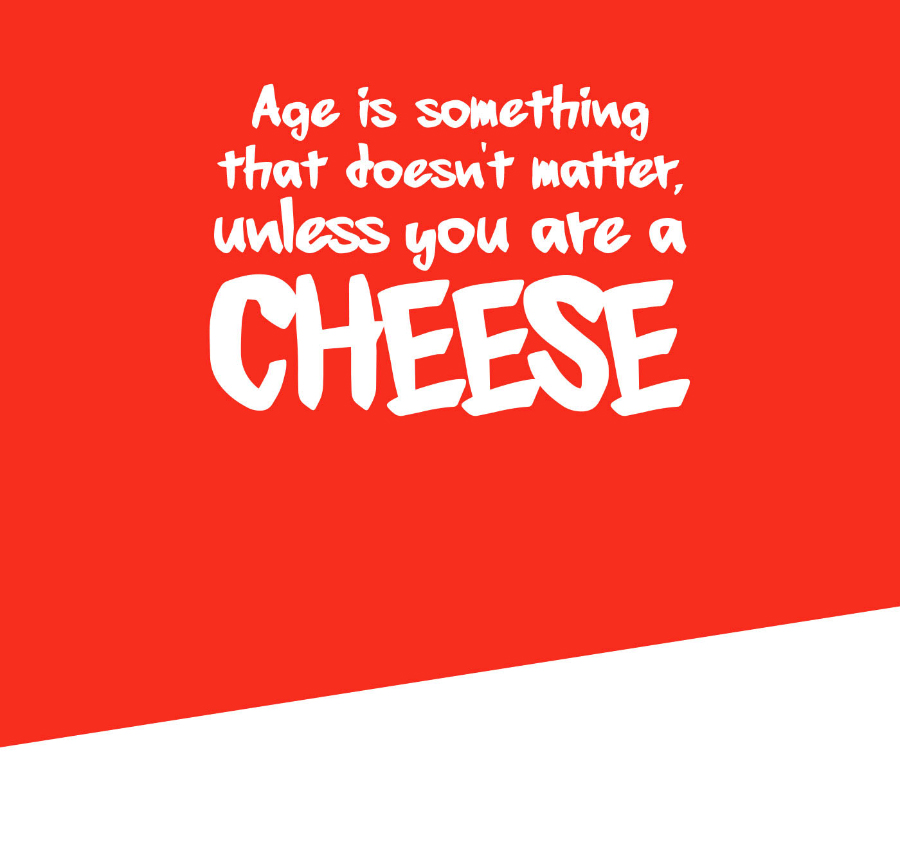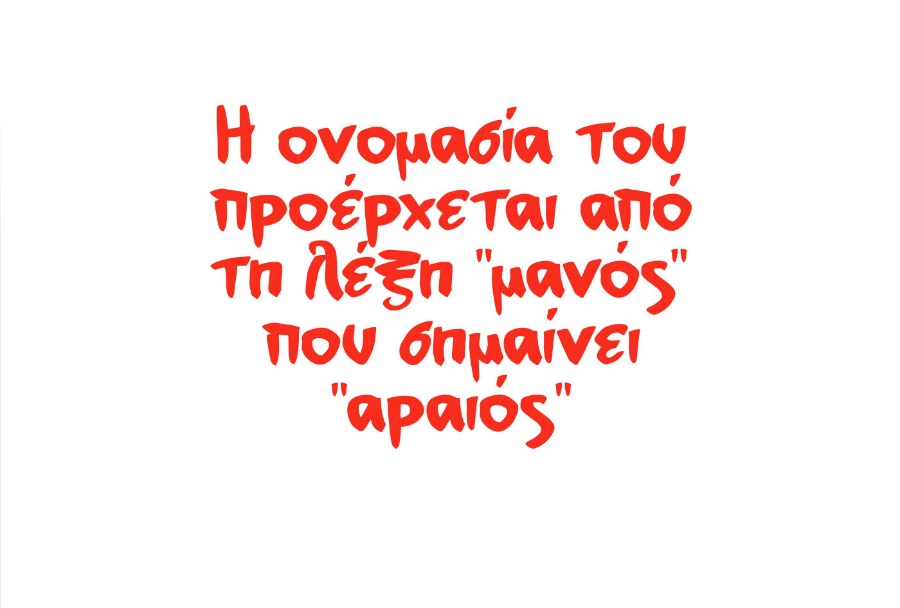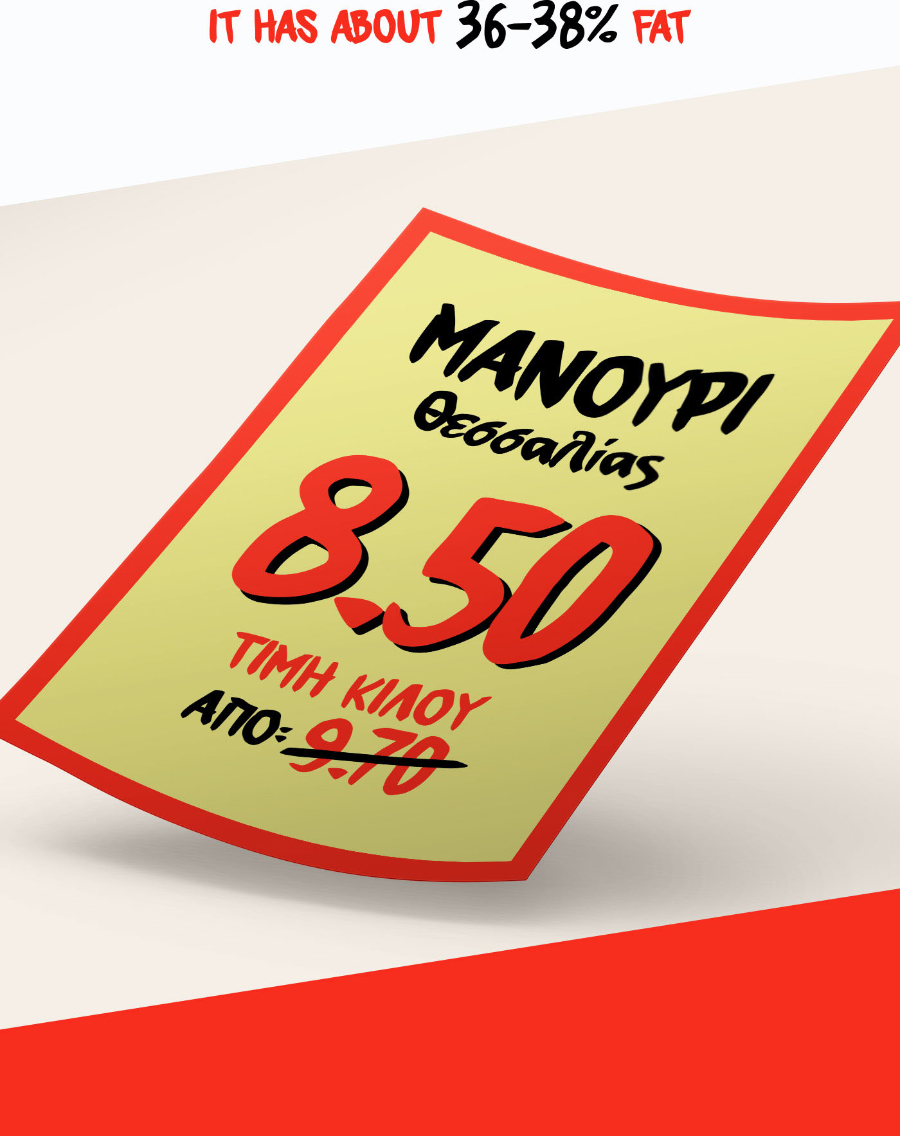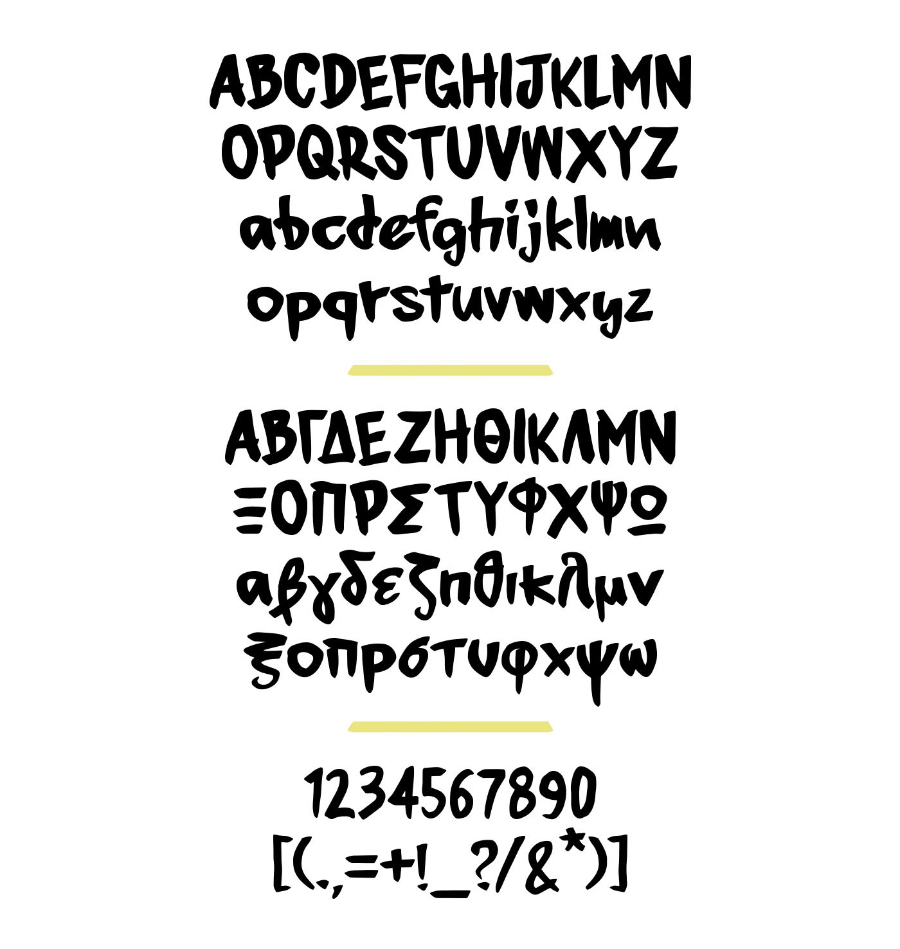
Manoyri自由标记字体
马诺伊自由标记字体!两位平面设计师Stergios Tsiamis和Iordanis Passas创造了一种叫做Manoyri的酷炫免费字体。这个字体为您呈现标记手写的真实外观。凭借其大胆的外观,使其成为关注的中心的完美。因此,Manoyri在广告横幅,标题,标志和品牌设计工作上都会很棒。